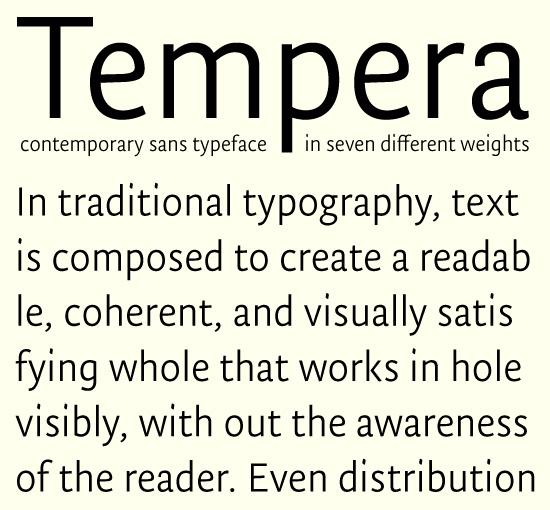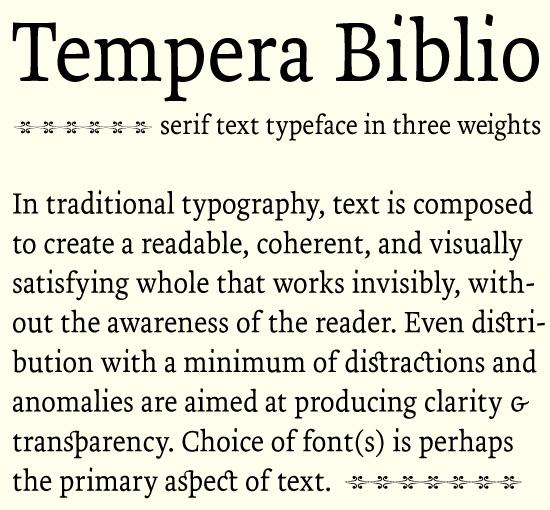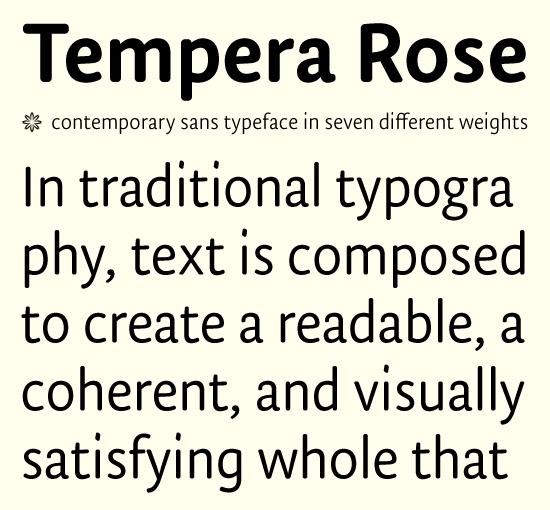
Tempera Family (TypoNine)
Designed by Nikola Djurek, 2008
Tempera Biblio is a contemporary serif typeface. It is designed for continuous
reading, therefore meant to be used for body texts. It is available in 3 text
weights which are matching with Tempera Book A, B and C weights. It contains
over fifty ornaments.
Tempera is a contemporary sanserif typeface available in 7 different weights.
Book A, B and C are matching weights with Tempera Biblio Book A, B and C.
Tempera Rose is a softer version of Tempera with slightly modified strokes and
rounded corners. It is a sans typeface available in 7 different weights.
Sind das jetzt Korinthen, wenn ich finde, dass man in einem Schriftmuster, wenn man ein «minimum of distractions» propagiert, gerade in das Wort «distractions» vielleicht nicht unbedingt eine ct- und eine st-Ligatur packen sollte? Oder lenkt Euch das nicht ab / fällt Euch nicht auf und ich bins bloß zuwenig gewohnt?
Mich stört es ebenfalls und im PDF-Schriftmuster vermisse ich
Mustertexte in Lesegrößen. Ein Text in 14 Punkt kann es ja
nicht sein wenn es um eine Leseschrift geht. Im übrigen finde
ich die i-Punkte bei der Biblio etwas irritierend - es scheint
als sitzen zu weit rechts.
Mich sprechen die beiden Serifinlosen auch eher an als die Biblio.
Die Grotesken haben ja auch diese rechtslastigen i-Punkte, aber bei einer Antiqua scheint mir das erträglicher. Ich würde halt gern mal einen längeren Text in der Biblio lesen, um zu sehen, ob das wirklich funktioniert oder ob das nach 10 Seiten gewaltig nervt.
Hmm. Die Schrift an sich gefällt spontan.
Die Biblio hat was von der Weidemann, aber nicht so Renaissance-lastig, die Sans etwas von einer Scala.
Die Würstchen-Version... weiß ich nicht. Ich mag die Art Schrift einfach nicht.